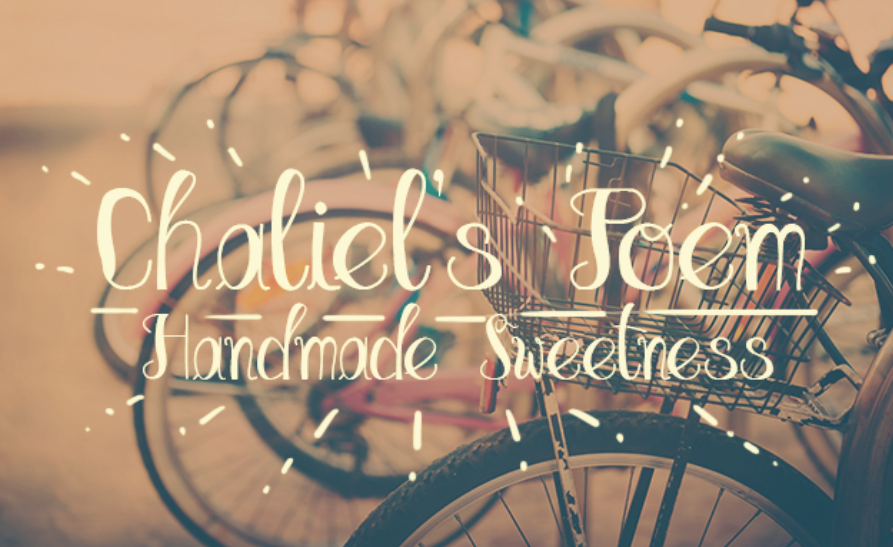
Chaliels Poem Script Font – Download Grátis
Introduzimos Chaliels Poem Font, uma nova fonte escrita a mão que inclui uma completa coleção de letras maiúsculas e minúsculas. Esta elegante fonte foi criada para atender às necessidades do branding, logomarca, convites, embalagens de produto ou simplesmente como um overlay estiloso de texto para qualquer imagem de fundo. Chaliels Poem oferece uma aparição natural e envolvente que vai se adequar perfeitamente a múltiplas aplicações visuais, dando seu projeto um toque único e sofisticado. Ideal para designers e artistas gráficos que buscam criar ambientes digitais com personalidade. Experimente Chaliels Poem Font hoje e transforme suas criações de design em verdadeiros momentos de arte.